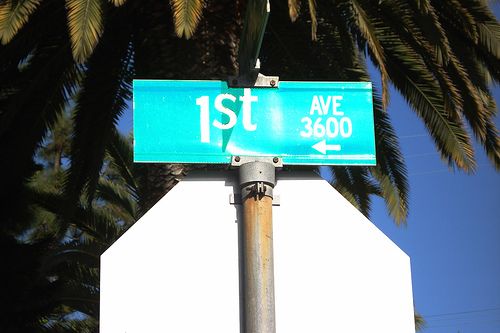
wird das „nd“ bei 2nd etc. hochgestellt?
kann, muss nicht. oder wie es die englische wikipedia ausdrückt:
“Formerly, these indicators were superscripts […] but by the late 20th century, formatting them on the line was favoured. The superscript style has, since the 1990s, been revived somewhat as some word processors format ordinal indicators as superscripts automatically.”
Wenn man die Möglichkeit des Hochstellens hat, dann sollte man diese meiner Meinung nach auch nutzen.
Wobei ich Zahlen bis Zwölf im Fließtext grundsätzlich ausschreibe. Bei den Ordnungszahlen verfahre ich da nicht anders. Ausnahme bilden natürlich Adelstitel, z.B. Arith, II. :)
Laut Detailtypografie werden diese Endungen nicht
hochgestellt. Ich persönlich finde es sehr unschön und
verstehe auch nicht warum man sie hochstellen sollte.
Warum? Weil es auf Fahrstuhlschildern einfach gut aussieht :party:
Dass man es zeitweise nicht hochstellte, ist doch mit Sicherheit wieder so eine technische Einschränkung der Schreibmaschinentypografie, oder nicht?
Ich würde es, wie bei so vielen Dingen, vom Text abhängig machen. Umso anspruchsvoller der Text und die Typo, umso eher würde ich auch die alte Form mit Hochstellung benutzen. Auf einem Popkonzertplakat sieht es aber wahrscheinlich wieder zu gestelzt aus.
... die alte Form mit Hochstellung ...
Kannst du mal näher erläutern warum die Hochstellung
die alte Form ist und welchem Zweck sie damals diente?
Vielleicht um die Basis der Ordinalzahl zu betonen. Bei 21nd ist ja die 21 wichtig, nicht das „nd“. Wenn im Text viele Ordinalzahlen vorkommen lässt sich das leichter erfassen. (Drum hab ich mich auch entschieden in meinem Fall das „nd“ nicht hochzustellen, weil nur eine Ordinalzahl im Text vorkommt).
... die alte Form mit Hochstellung ...
Kannst du mal näher erläutern warum die Hochstellung
die alte Form ist und welchem Zweck sie damals diente?
Na das liegt doch auf der Hand. Es kommt nicht von der Abkürzung des Zahlwortes, sondern leitet sich direkt von der arabischen Ziffer ab. Um zu betonen, dass es nicht »zwei«, sondern »der zweite …« bedeutet, benutzt man eine dezente Lesehilfe – bei uns der Punkt, im Englischen eben die hochgestellte Endung.
Das ist natürlich wie so vieles einfach eine reine Konvention – ein Streit, welche Variante falsch oder richtig ist, kann es nicht geben.
… Bei 21nd …
21nd gibt es doch gar nicht, das muß doch 21st heißen, oder?
:| ist noch zu früh am Tag… war auch nur ein Beispiel.
Das ist natürlich wie so vieles einfach eine reine Konvention – ein Streit, welche Variante falsch oder richtig ist, kann es nicht geben.
Mich interessiert nur welche Version es zuerst gab und
warum das die hochgestellte gewesen sein soll! Das muss
sich doch belegen lassen oder?
Dass man es zeitweise nicht hochstellte, ist doch mit Sicherheit wieder so eine technische Einschränkung der Schreibmaschinentypografie, oder nicht?
Sehr wahrscheinlich. Wobei es auch zu der Zeit hin und wieder Schreiber gab, die dann die Walze immer wieder einen Knack hoch gedreht haben.
Heute scheint die nicht hochgestellte Variante in fast allen Anwendungen (also auch auf Straßenschildern) zumindest hier in Nordamerika aber wieder/immer noch (?) die häufigere zu sein. Sicher auch, weil das bei elektronisch erzeugten Druckvorlagen einfach einfacher ist.
Der Grund warum ich das nochmal nachgelesen hatte bei Forssman/de Jong war, weil es ein Änderungswunsch in der Copy war. Meinem Empfinden nach sieht es, zumindest in dem konkreten Fall, nicht hochgestellt besser aus.
Ich mache das immer nach Aussehen. Was in einem einzeiligen Schild schick aussehen mag und für Klarheit sorgt (denk’ nur an 1st ave & 2nd st – heißt st da nun street oder (fir)st?), reißt im mehrzeiligen Fließtext schnell hässliche Lücken.
Beide Varianten sind weit verbreitet und richtig.